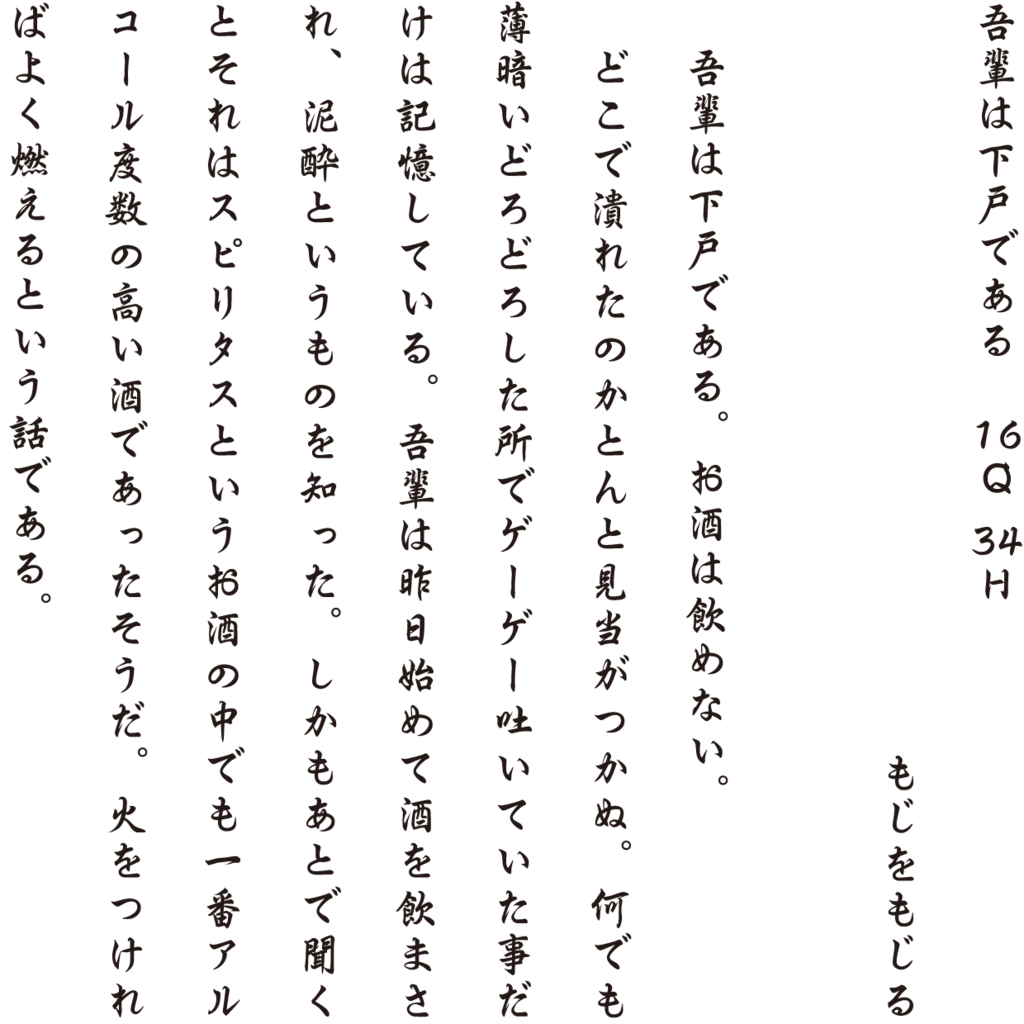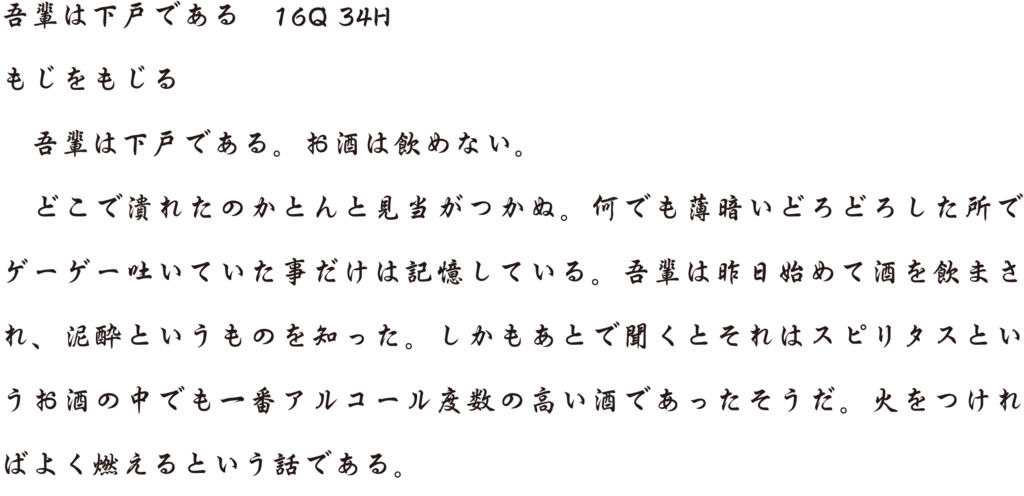
結婚式 招待状 書体. こちらの記事ではブライダルシーズンに向けて ウェディング用の無料フォント をご紹介しております。 ウェディングの招待状デザインの工程を手軽にするために、 ウェディング用の無料フォント の中から使いやすく、人気のフォントを選びました。. 「結婚式の宛名書き」に自信がない…! プレ花嫁のみなさん、結婚式の招待状の「宛名書き」はどうする予定ですか?宛名書きの方法は、 ☑筆耕を頼む ☑印刷をする ☑自分で書く の3種類。 招待状はゲストに渡す1番最初のおもてなし。. 結婚式の招待状。 ゲストの名前と住所は、自分で書く or 筆耕を頼むのが主流でしたが、今は封筒への印刷でもok。マナー的にも問題ありません* そこで、宛名をwordで作って印刷にかける場合。 いったいどの書体(フォント)を選べばいいのでしょうか?.
結婚式の招待状を印刷する際 皆さんが迷いがちなポ 結婚式の招待状の差出人の住所は? 書き方のマナーについても|ブライダルフェアから始まる結婚式の悩みを解決するサイト. - ウェディングなど招待状・案内状・賞状などをおしゃれでエレガントに飾る英字フォント 筆記体など高品位なデザイン文字が勢揃い! wedding-script-font. パソコンの標準フォントは結婚式の招待状には使うには少しダサいですよね。 そこでおすすめがフリーフォントの活用です。 無料でもおしゃれなフォントはたくさんあるので、ぜひ活用したいところですが、初めてフリーフォントを使う人に ….
招待状やウェルカムボードに使ったときのイメージがわくように、「Welcome to our wedding」を各フォントで作成しているので、参考にしてみてください☆. 結婚式の招待状にクラシカルな見た目を探しているときに、ぴったりなフォントの組み合わせ。Pinyon Script は結婚式にぴったりな高級感のある見た目で、Forum のようなセリフ書体に、金色テクスチャを合わせると良いでしょう。 Pinyon Script をダウンロード.